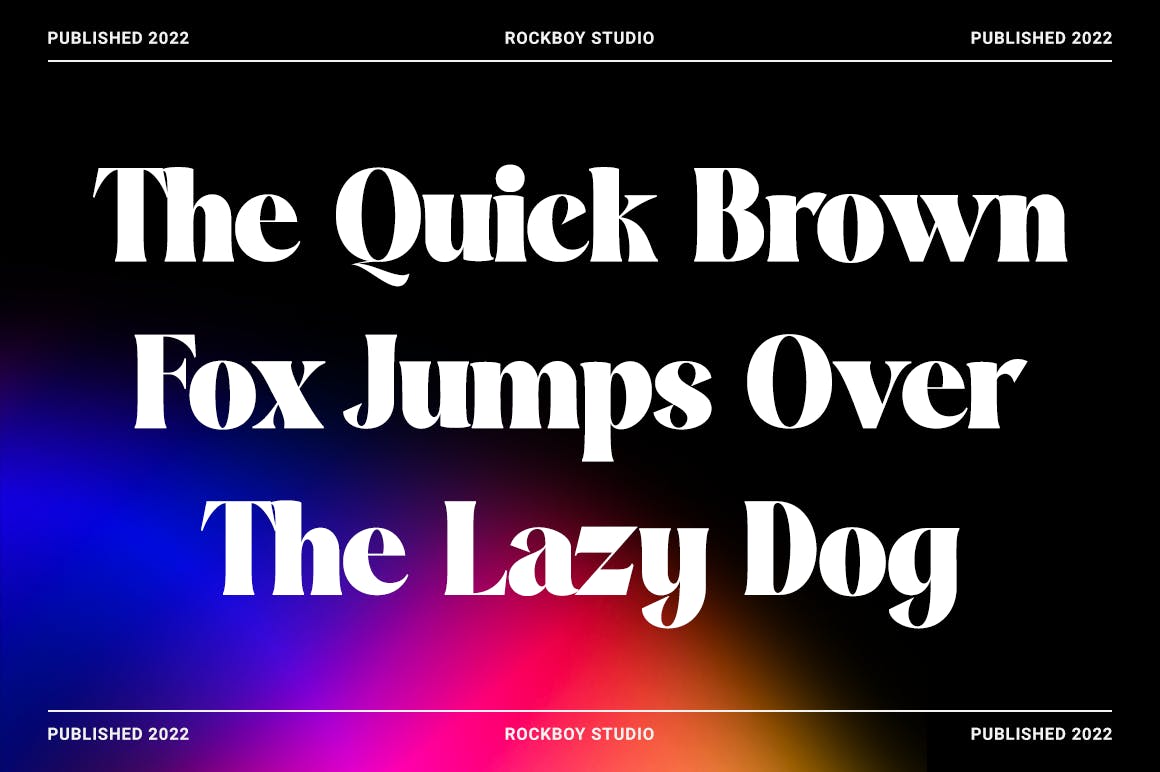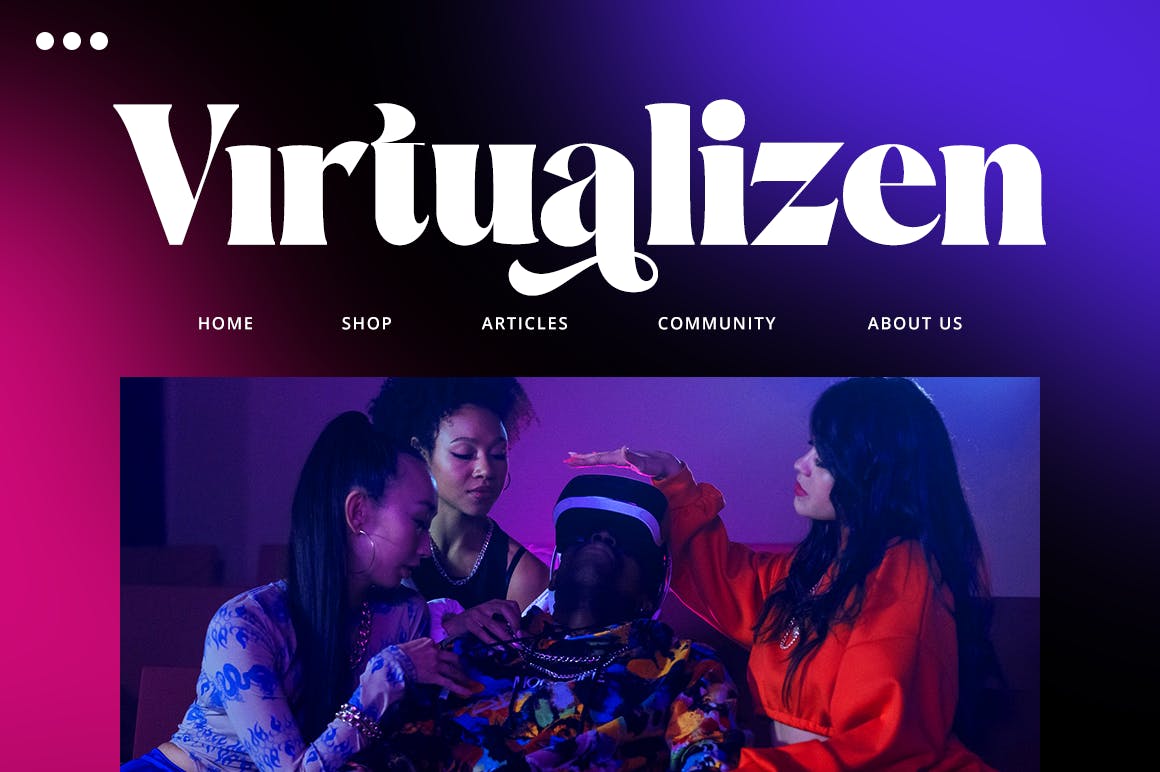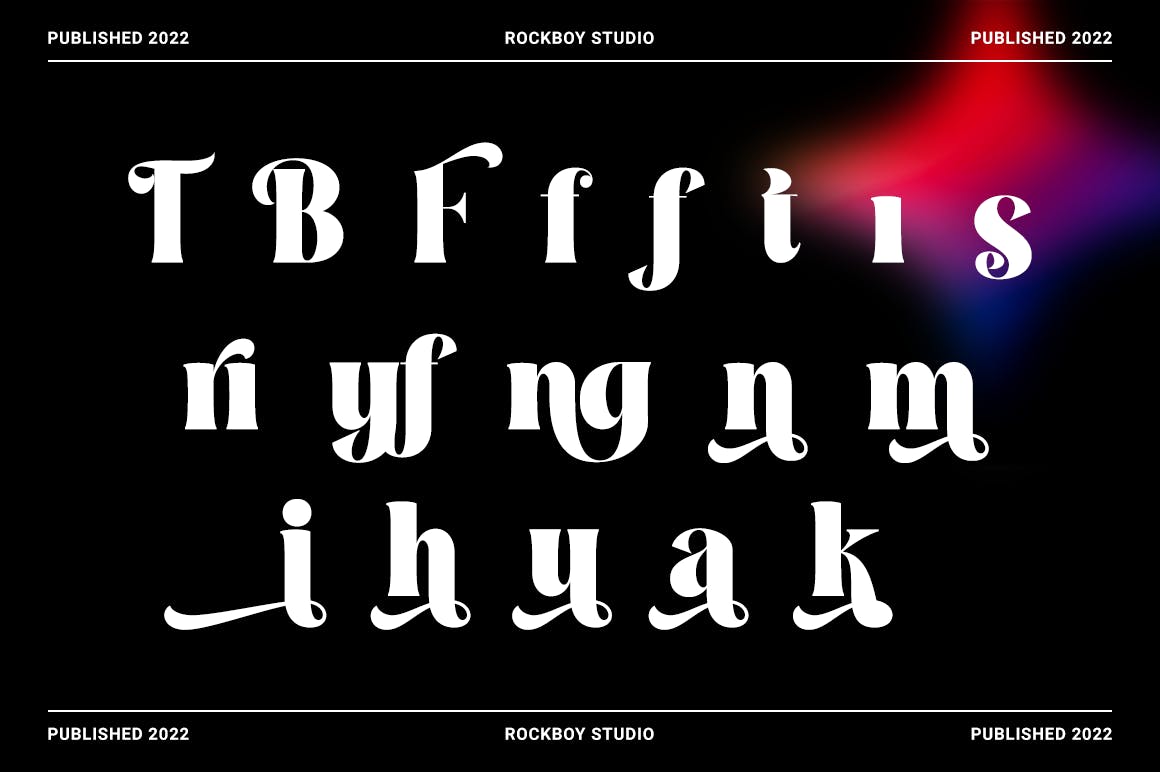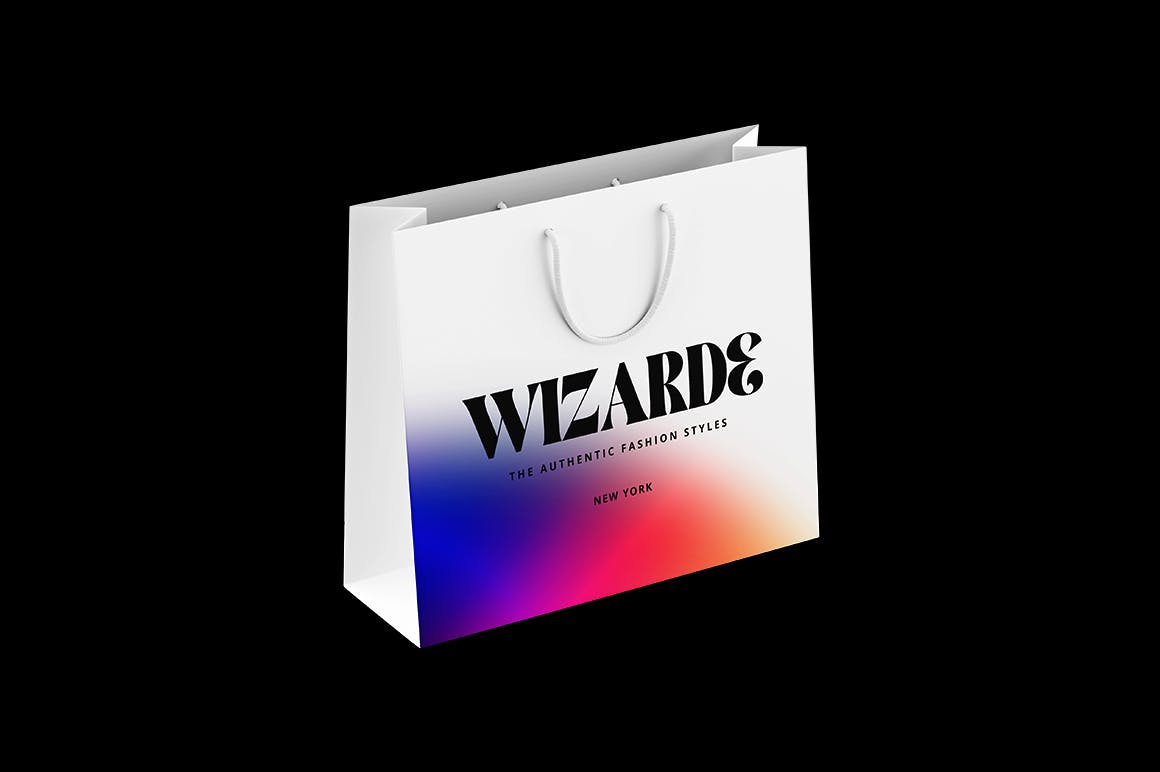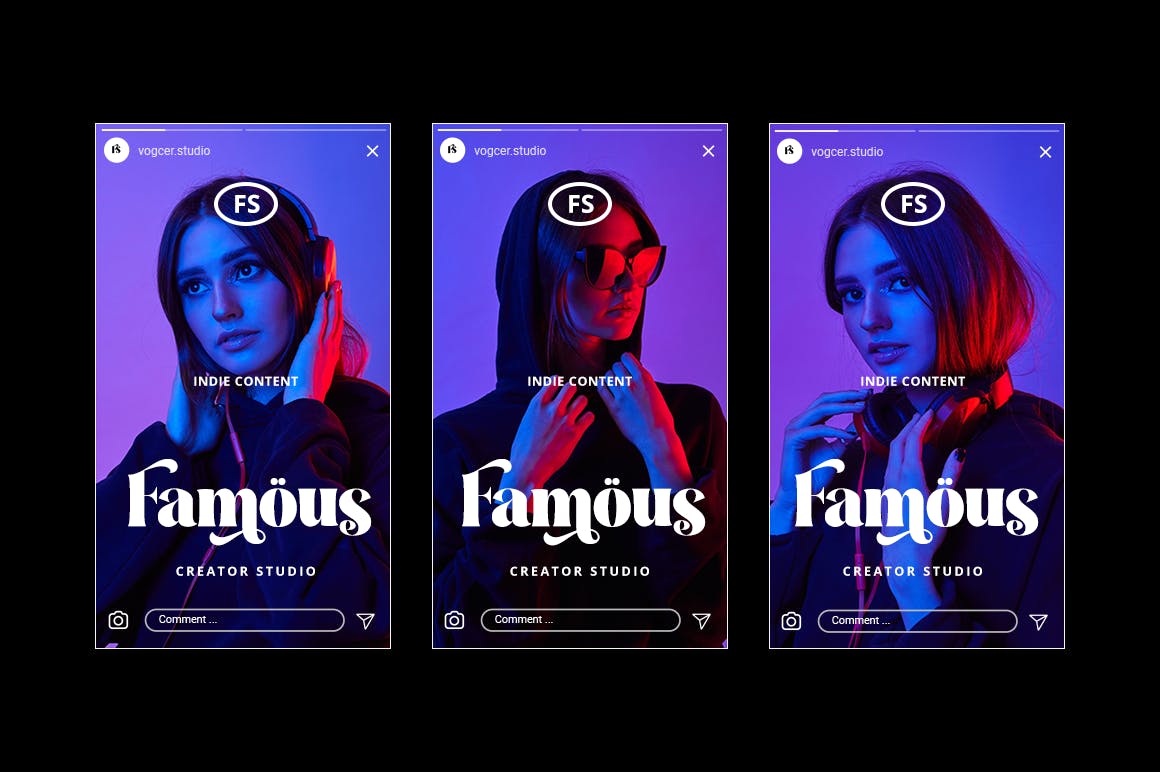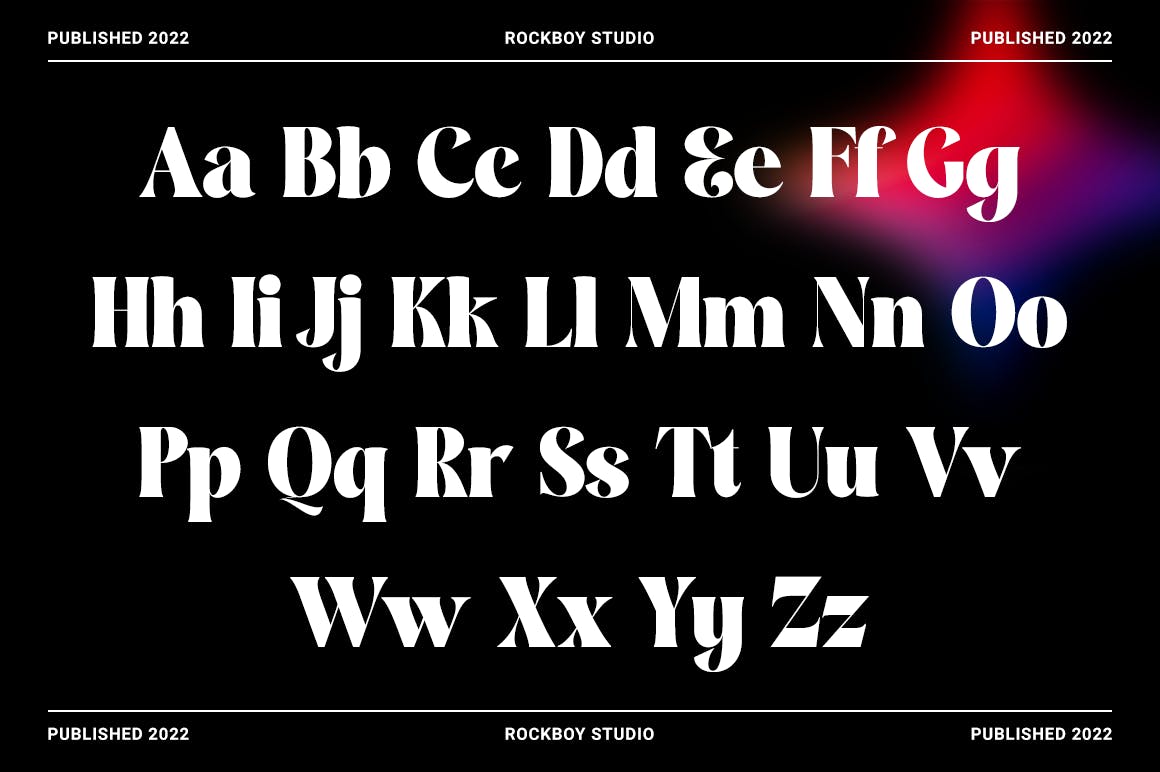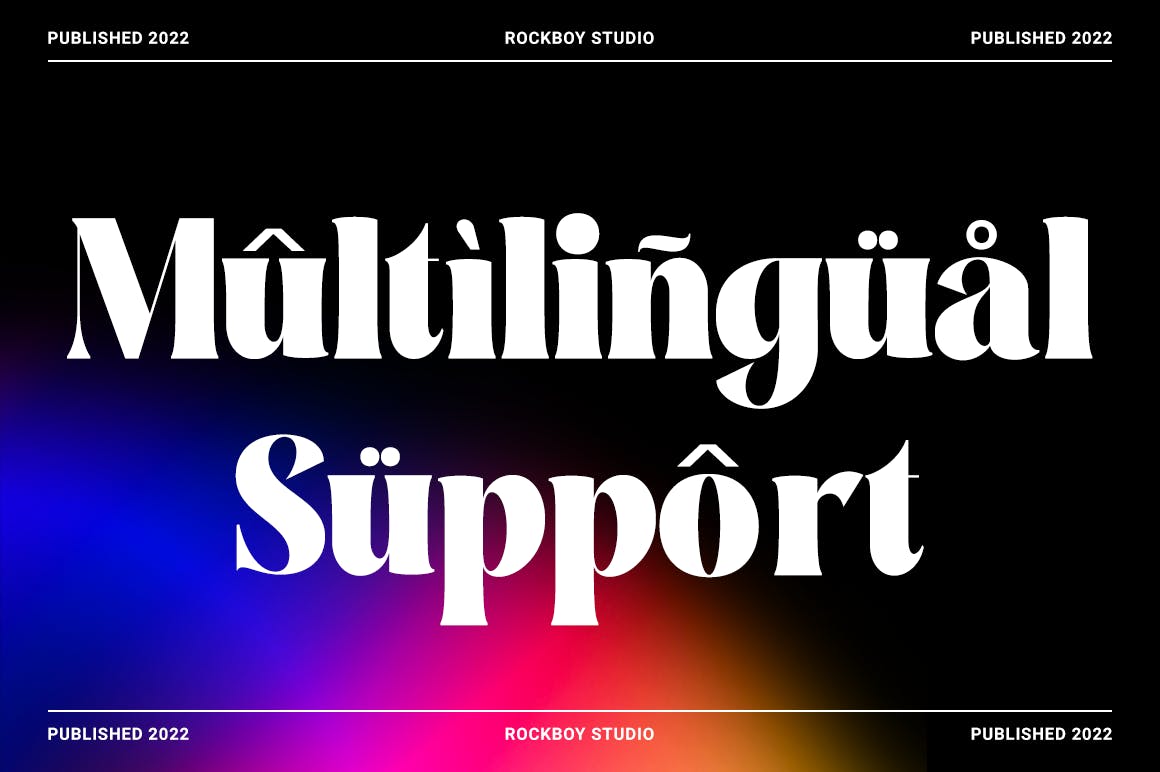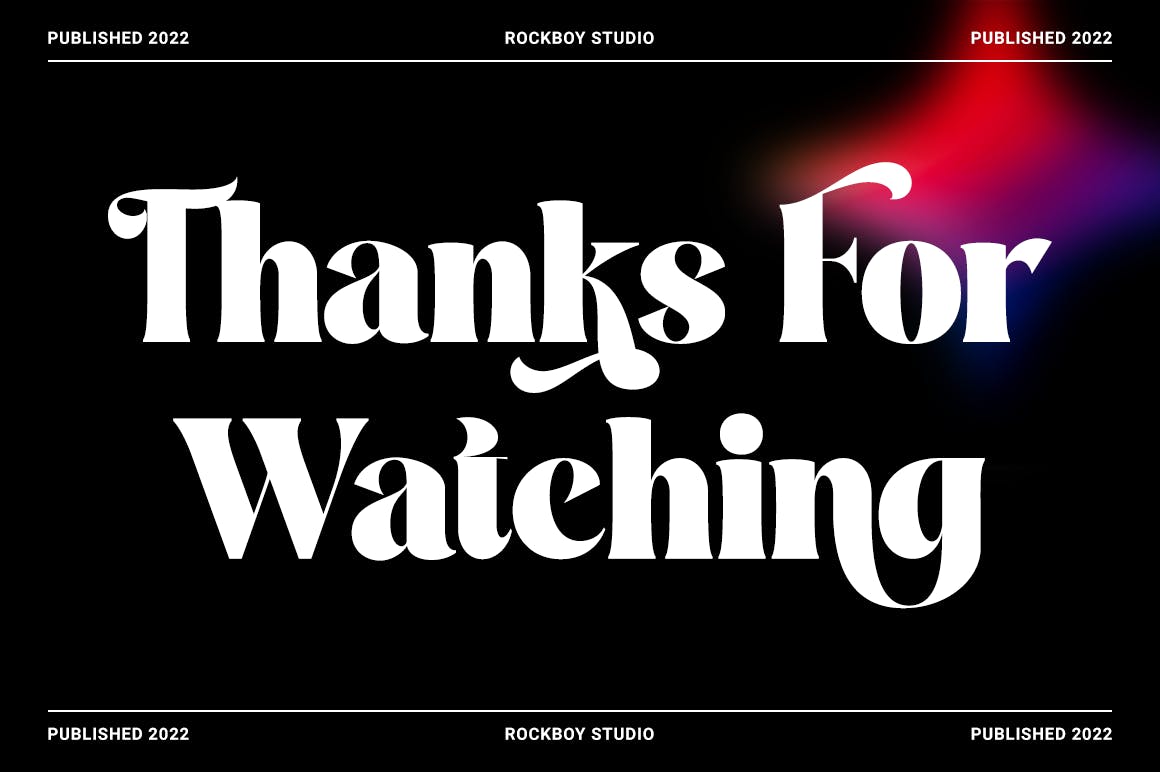
Fariative یک فونت serif با طراحی زیبا و منحصر به فرد است. این فونت به دلیل سبک مرتب و سادهاش، برای انواع طراحیها مناسب است و میتواند به فونت مورد علاقه شما تبدیل شود، صرفنظر از موقعیت!